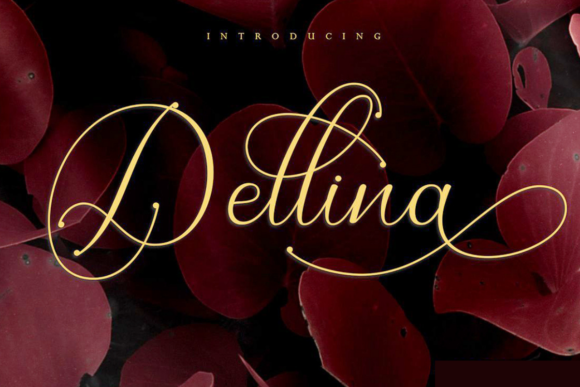
Dellina Script
Если вы ищете высококачественные ресурсы, такие как Dellina Script, этот премиум-пакет — фантастический выбор для ваших творческих проектов.